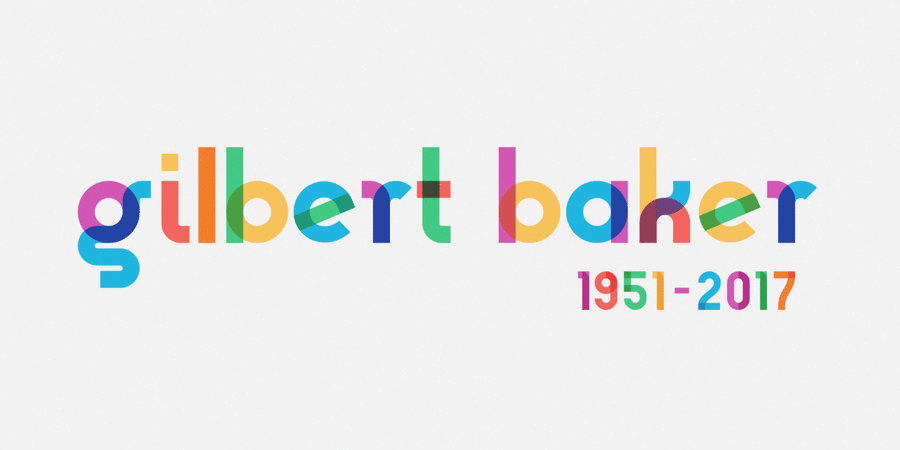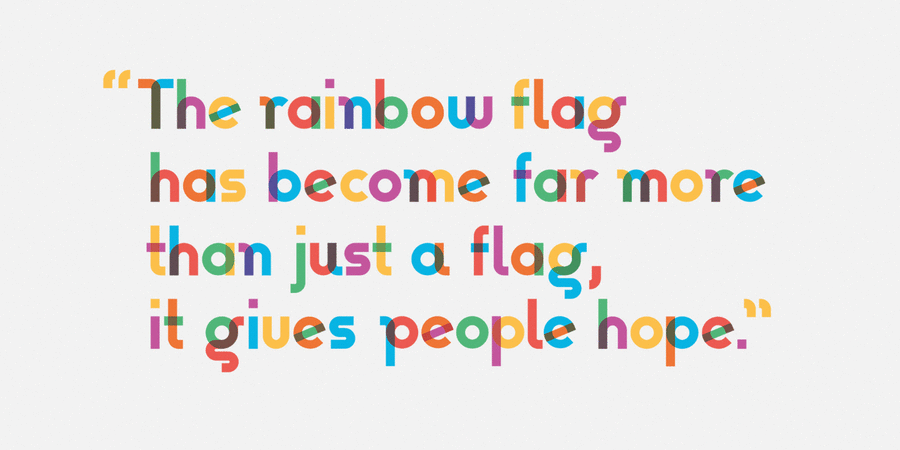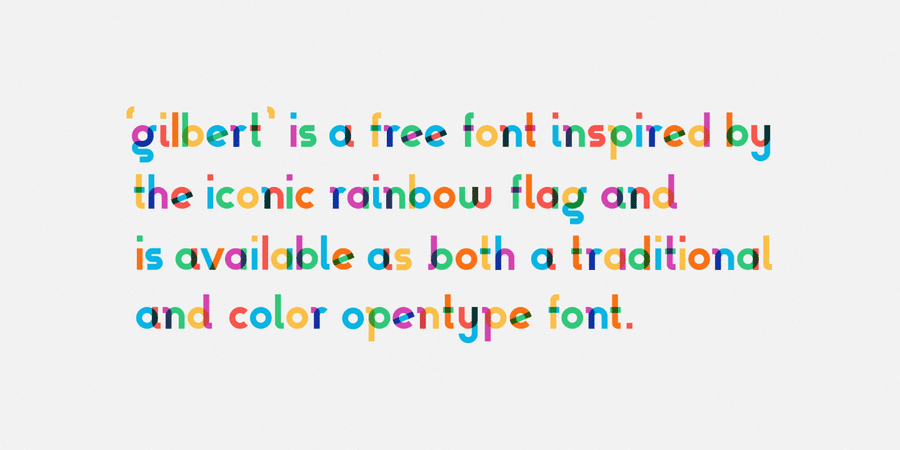
Шрифтова пара з Skema Pro Title Light (1 з 3)Опис шрифта Gilbert31 березня 2017 помер Гілберт Бейкер – творець знаменитого Райдужного Прапора. Він був активістом LGBTQ, художником, і був відомий тим, що допомагав друзям створювати банери для протестів і маршів. Щоб вшанувати пам'ять Гілберта Бейкера, NewFest і NYC Pride разом з Ogilvy & Mather і творцями шрифтових інструментів Fontself випустили безкоштовний шрифт за мотивами Райдужного Прапора. Цей шрифт був названий «Gilbert» на честь Гілберта Бейкера.
Шрифт Gilbert призначений для яскравих заголовків та гасел на банерах для мітингів і протестів. Демо-версія Gilbert доступна на сайті typewithpride.com у двох варіантах: стандартного векторного OpenType шрифту, який можна використовувати у будь-якій програмі та кольорового шрифту OpenType-SVG, який можна використовувати у Photoshop CC 2017.
Символи шрифту створювалися в Illustrator CC, а потім вони були перетворені на файли шрифтів за допомогою спеціального плагіну для створення шрифтів Fontself for Illustrator, адаптованого спеціально для генерації кольорових векторних шрифтів.
Асоціації з сімейством шрифтів GilbertОсобистість і характер гарнітури:
амбітний, сильний, сміливий, креслярський, гладенький, наївний, чіткий, машинний, промисловий, елементарний, круглий, цікавий, активний, твердий, залізний, надійний, мужній, впевнений, сталевий, грубий, гучний, рівний, динамічний, революційний, важливий, індустріальний, техногенний, кольоровий, різнокольоровий, монументальний, урбаністичний, робочий, мотивуючий, крутий, гнучкий, рухливий, міський, чистий, модний, оригінальний, вільний, виразний, гордий, лаконічний, молодіжний, дзвінкий, позитивний, артистичний, сучасний, клубний, святковий, музичний, точний, свіжий, неоновий, яскравий, помітний, тусовочний, веселковий, театральний, грайливий, танцювальний, інженерний, нічний
техніка, верстат, інструмент, завод, тренажери, Місто, креслення, інженер, архітектура, металургія, мотор, урбаністика, конструктор, електроніка, авто, залізо, сталевар, будматеріали, будівництво, прапор, мітинг, парфумерія, туалетна вода, мода, інтер'єр, театр, одяг, телебачення, шоу, музика, естрада, нічний клуб, дизайн, розваги, атракціон, гра, клуб, дискотека, кіно, мюзикл, бар, алкоголь, коктейль, свято, вечірка, тусовка, суспільство, ЛГБТ, танці, прилад, Трофей, нагорода, робочий, страйк, Протест, рок-н-рол, аквадискотека, кінотеатр Гарнітура асоціюється з віком: